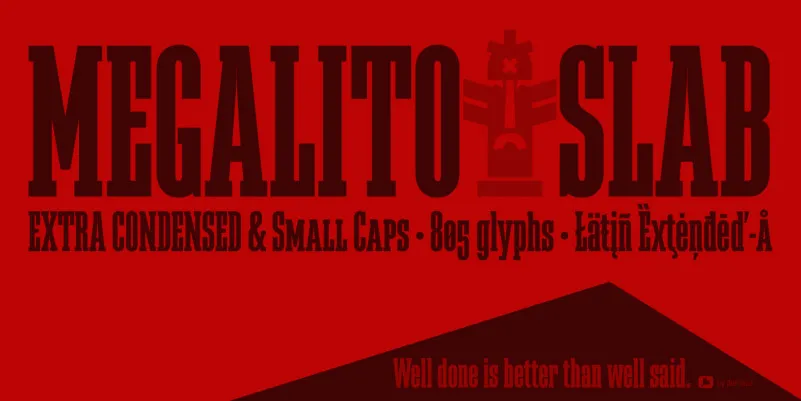
Megalito Slab & Small Caps Font – Fonte Grátis
Megalito Slab & Small Caps Font
A fonte Megalito Slab & Small Caps é uma escolha ideal para aquelas criações que exigem uma presença dramática e visualmente atraente. Ela se destaca por sua construção geométrica, com linhas verticais muito marcantes que proporcionam um desenho vertical, perfeito para criar grandes títulos com economia de espaço horizontal significativa. Essa característica é particularmente útil para ambientes digitais onde espaço e eficiência são fundamentais. Mas o verdadeiro segredo da Megalito reside no seu extenso conjunto de caracteres (805 glifos), que inclui tanto letras minúsculas quanto os 7 conjuntos numéricos, incluindo símbolos de frações dinâmicos junto com números e letras. O catálogo de sinais monetários, ligaduras e alternativas de letras adiciona ainda mais uma variedade impressionante a esta fonte sofisticada. É perfeita para criar títulos chamativos em qualquer formato, seja eletrônico ou impresso, tornando-a uma escolha inegável para designers proeminentes no mercado brasileiro.